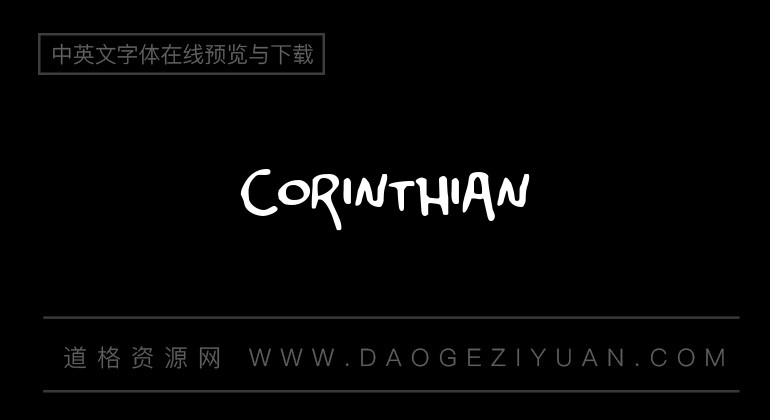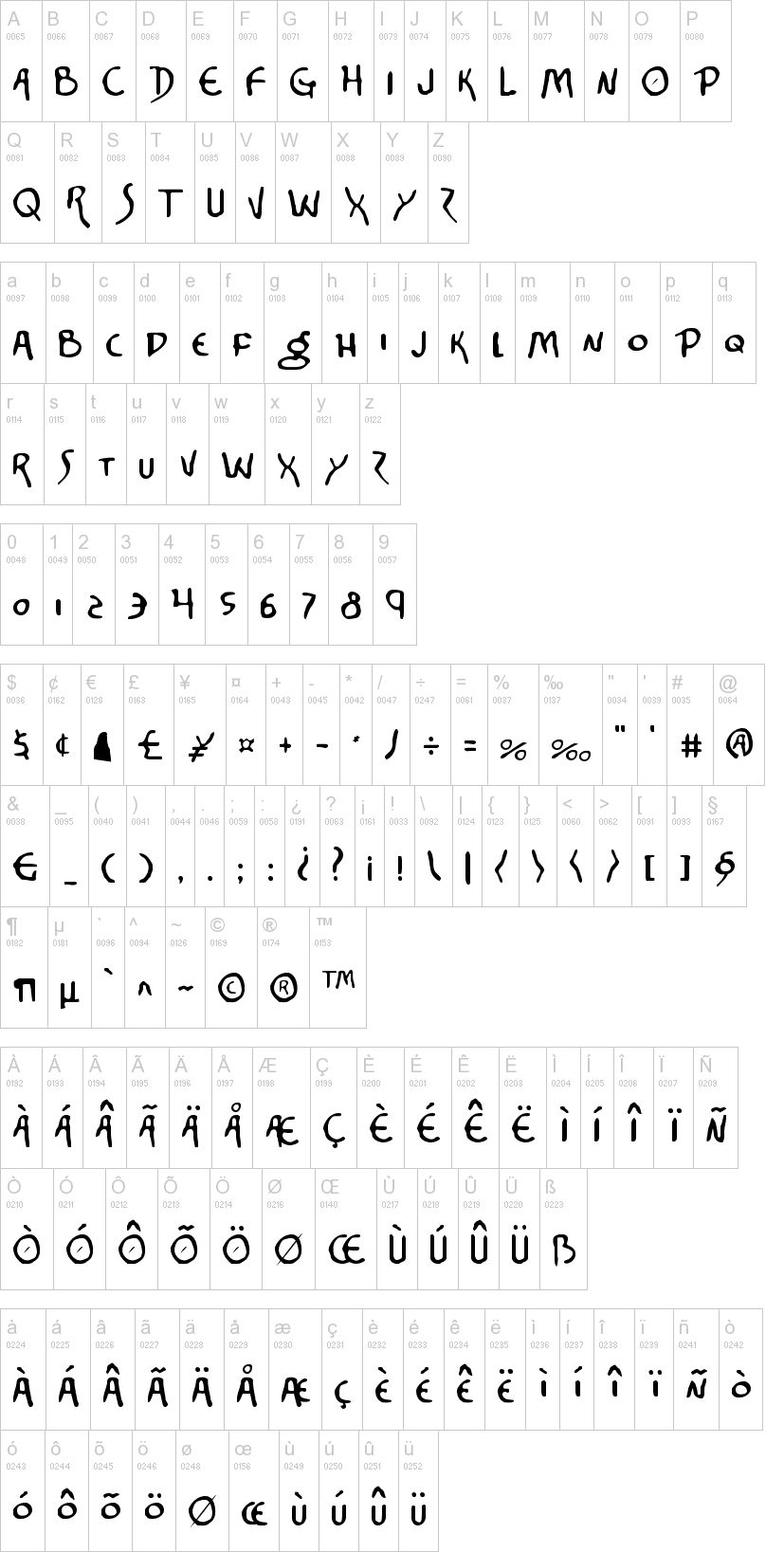
Corinthian
? Corinthian 字体是一种细腻、优雅的英文字体,它的字母形状经过精心设计,具有流畅的线条,柔和的曲线,细节精致,具有英文字体的质感。这种字体特别适合用于设计精美的海报、书籍封面、印刷品等。它也适用于网页设计,可以为网页提供优雅而有质感的字体效果。
Corinthian是一款非常不错的手写艺术字体,具有很好的视觉感,适合于文化类的宣传设计、商业类品牌的广告和产品包装设计以及个性化文字排版等较多场景。
Corinthian字符映射图